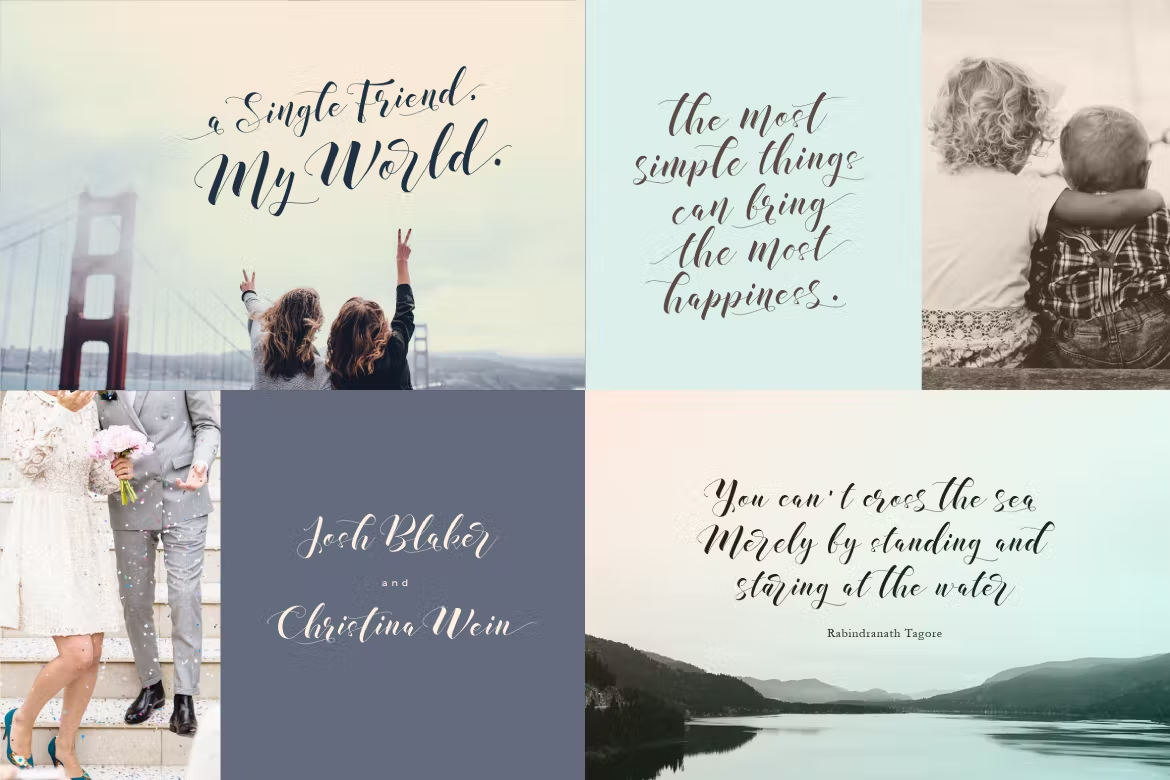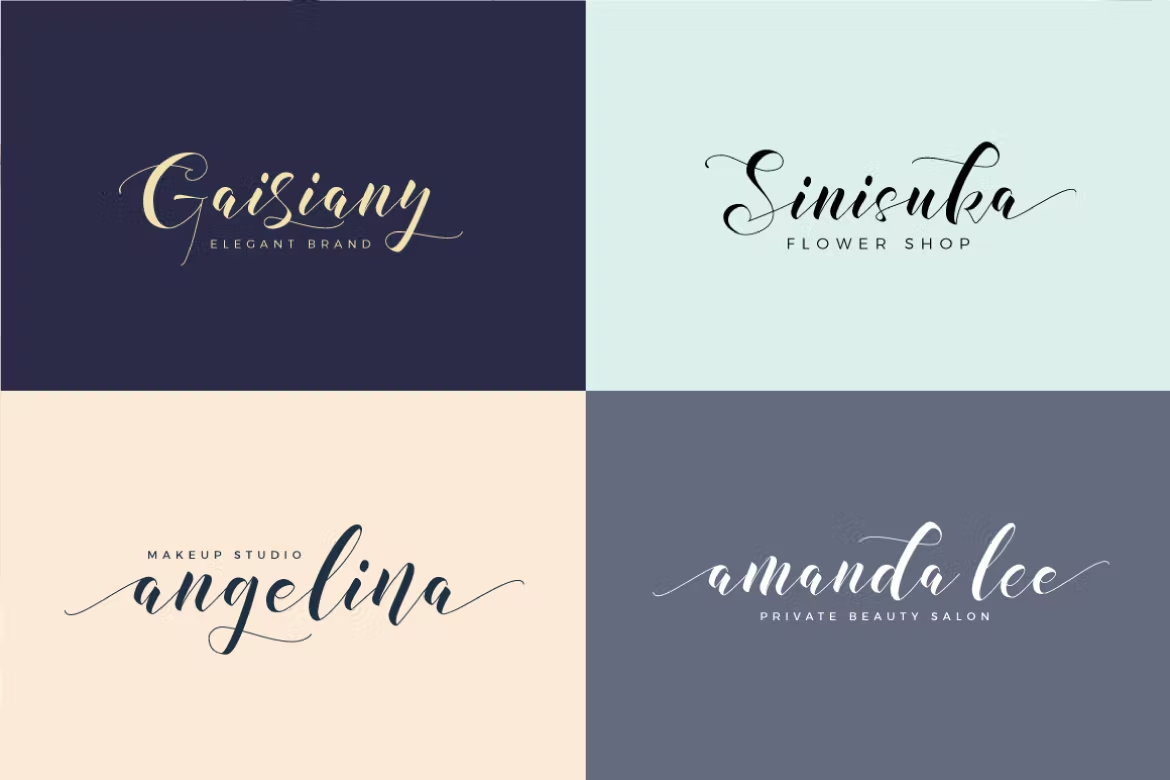
illusias Font
illusias est une police manuscrite élégante.
La police illusias convient à tous les besoins de conception, conception d’invitation moderne, image de marque, conception de blog, conception de publicité moderne, invitation, citation d’art, décoration intérieure, titre de livre/couverture, invitation, événements spéciaux, anniversaire, tasse personnalisée, oreiller, t-shirts , tous vos besoins en matière de lettrage au pinceau et bien plus encore.
La police illusias (.ttf et .otf) est livrée avec des caractères standard majuscules et minuscules, de la ponctuation et des chiffres. Et d’autres variantes de glyphes des fonctionnalités OpenType telles que la ligature standard, l’alternance stylistique et l’ensemble stylistique (ss01, ss02, ss03) et Swash. Accessible dans le panneau Adobe Illustrator et Adobe Indesign Glyphs, ou sous Alternatives stylistiques dans le menu Adobe Photoshop OpenType.